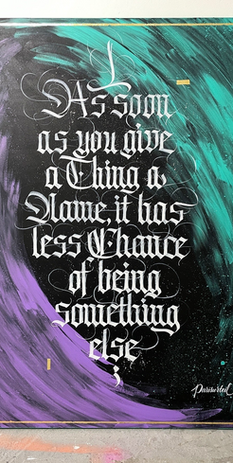
Parisurteil | Johannes Schleicher
Ich bin Berliner Kalligraph und Urban Artist. Meinen ersten richtigen Kontakt mit Kalligrafie hatte ich 2015, als ich ein Video sah, in dem ein CD-Cover von Frank Ortmann gestaltet wurde – und seitdem hat mich das Thema nicht mehr losgelassen. Ich begann, frenetisch zu schreiben und bald stellte sich heraus, dass ich eine tiefe Liebe zu Frakturschriften habe.
Da ich in Berlin lebe, ist die Verbindung zur urbanen Kunst ziemlich naheliegend. Es gibt eine Menge legaler Wände in dieser Stadt, die urbane Kunstszene ist riesig und sehr herzlich. Da Kalligrafie – zumindest Breitfeder-Kalligrafie – leicht skalierbar ist, habe ich schnell angefangen, auf Wänden zu schreiben. Ich liebe den Kontrast zwischen dem sauberen und akkuraten Schreiben auf handgeschöpftem Papier und dem Ausrasten auf einer riesigen Wand, wo überall Farbe spritzt. Beide Formen der Kalligrafie sind für mich absolut faszinierend.
Noch eine kurze Bemerkung zu meinem Künstlernamen "Parisurteil": Ich wünsche der Stadt Paris nichts Böses – der Name spielt auf einen griechischen Mythos an, in dem der trojanische Prinz Paris die schönste Göttin wählen soll und dafür nicht nur Helena, die schönste Frau der Welt, bekommt, sondern auch Troja in den Untergang stürzt. Das als Allegorie für die Entstehung und Wahrnehmung von Kunst zu verwenden, erschien mir passend: Jedes Urteil (Meinung) hat verschiedene Aspekte und verschiedene Konsequenzen, sowohl das Urteil über das Kunstwerk als auch das Kunstwerk selbst: Jedes Kunstwerk ist ein Urteil über die Welt.